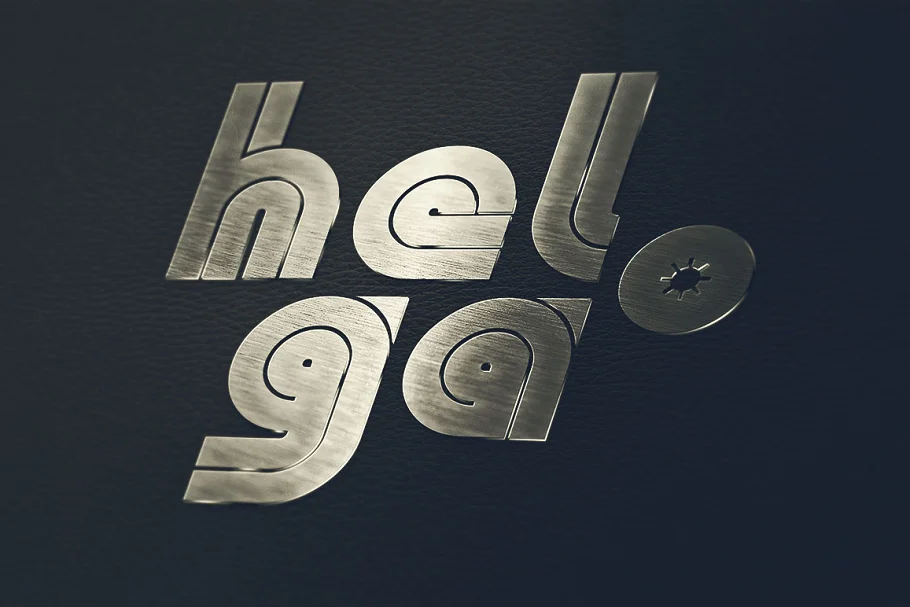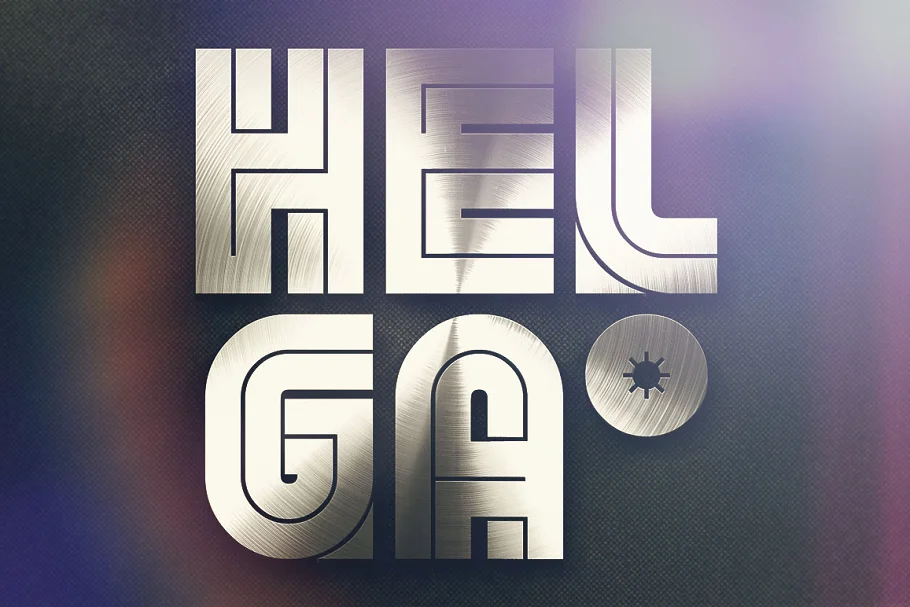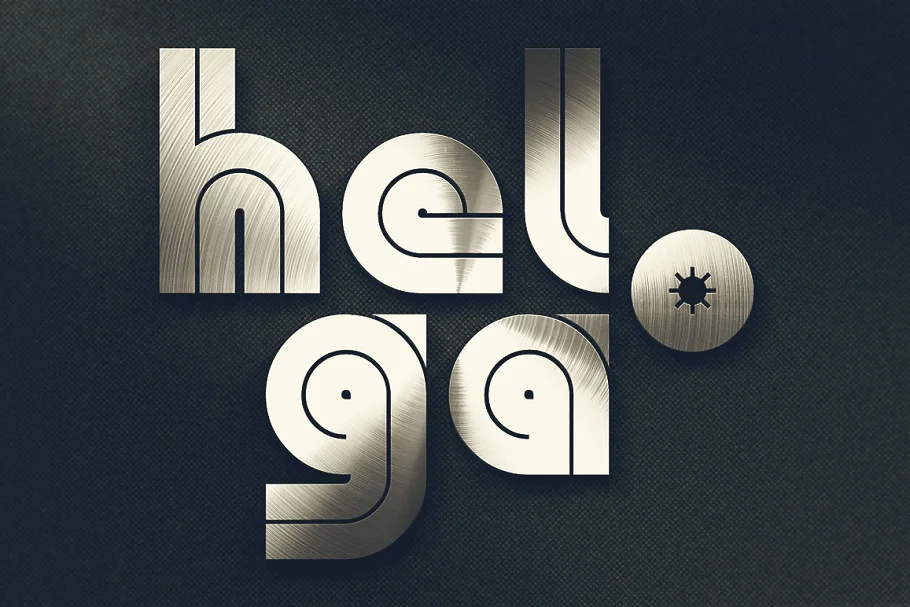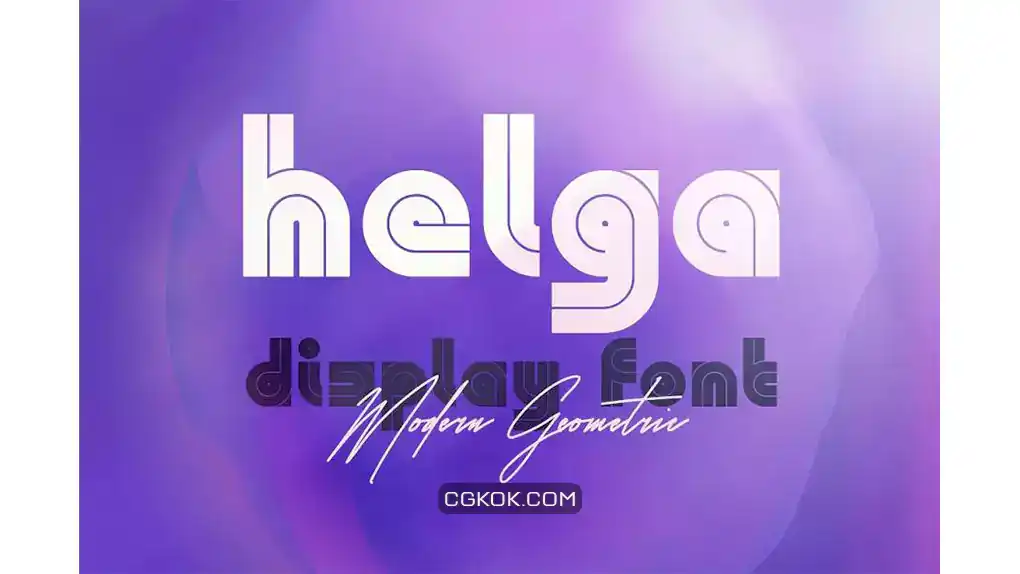
فونت انگلیسی گرافیکی Helga – Display Font : این مجموعه شامل یک فونت انگلیسی هندسی و مدرن است که برای پروژه های سبک مدرن مناسب میباشد. فونت های گرافیکی می توانند جذابیت طرح های شما را چندین برابر کنند، در دسته بندی فونت انگلیسی گرافیکی در سیجی کوک می توانید فونت های گرافیکی بیشتری را دانلود کنید.